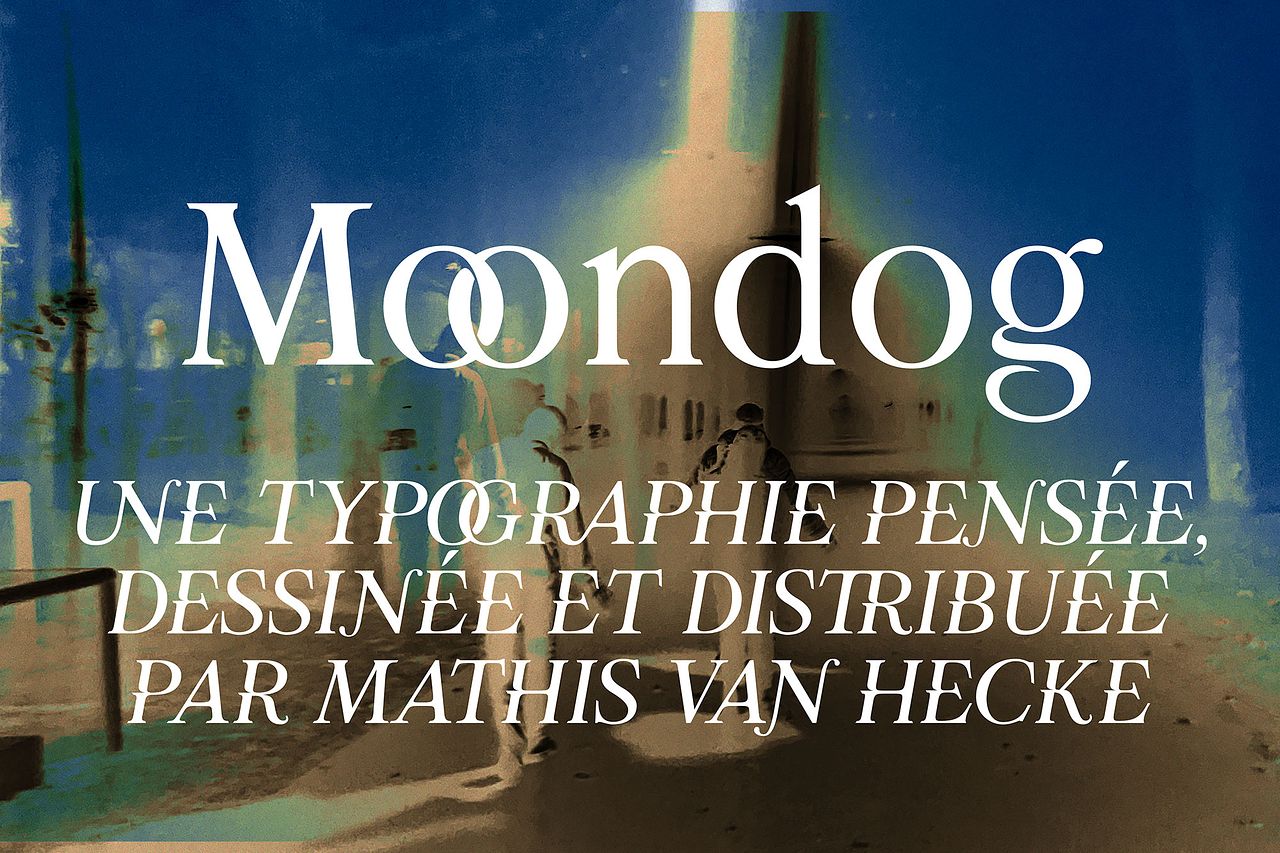
Moondog — typeface
Police de caractère à empattements inspirée des typographies de la famille des réales telles que Times New Roman. Des courbes viennent cisailler certaines lettres en leur centre dans l’objectif de donner une finesse supplémentaire.